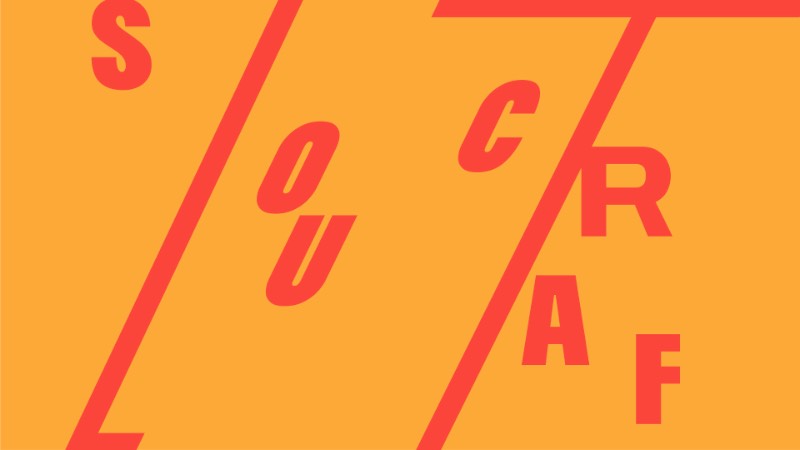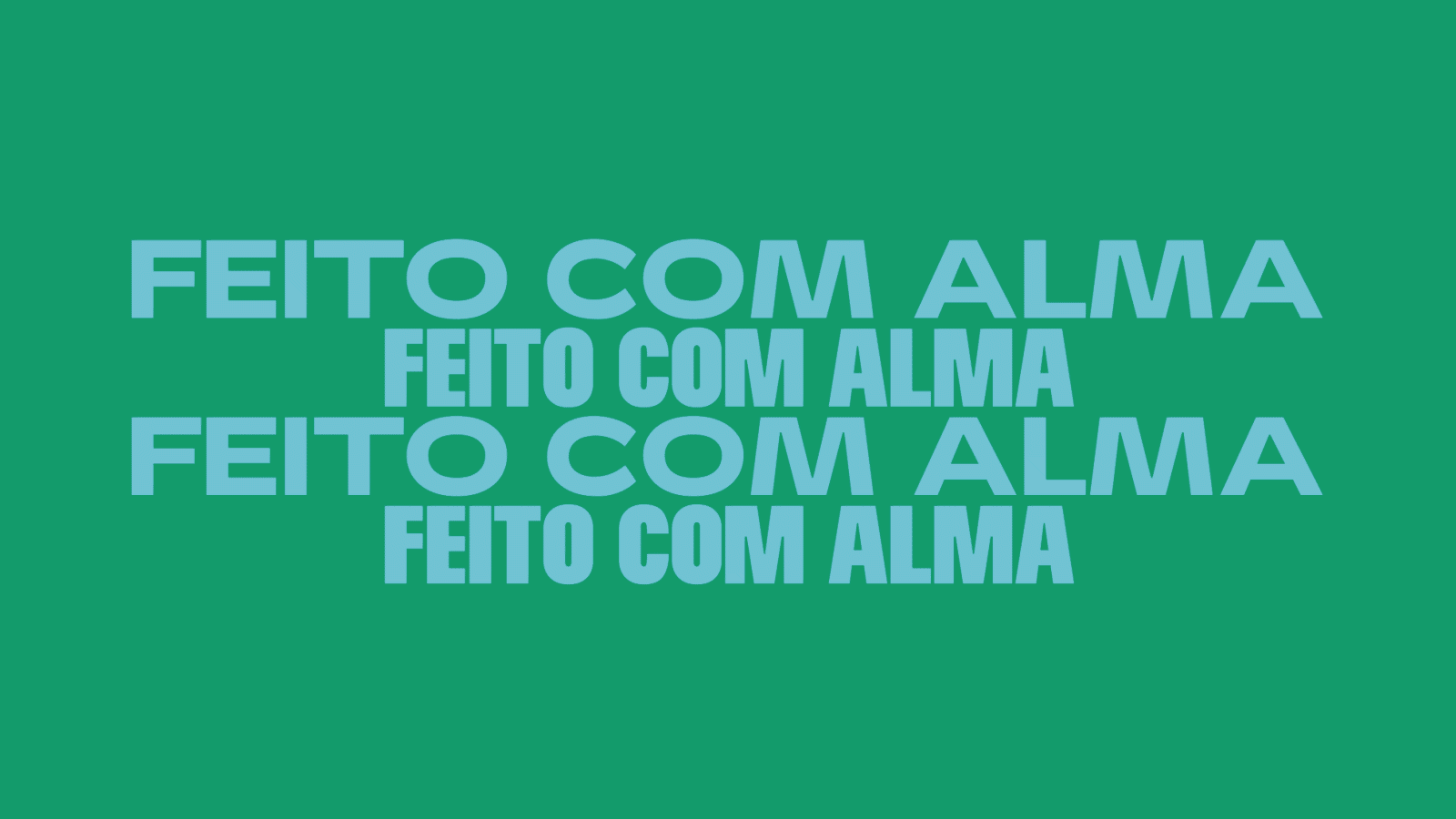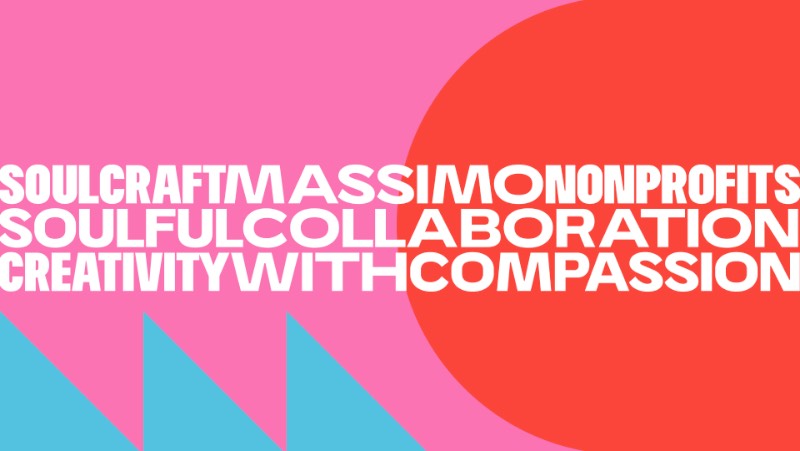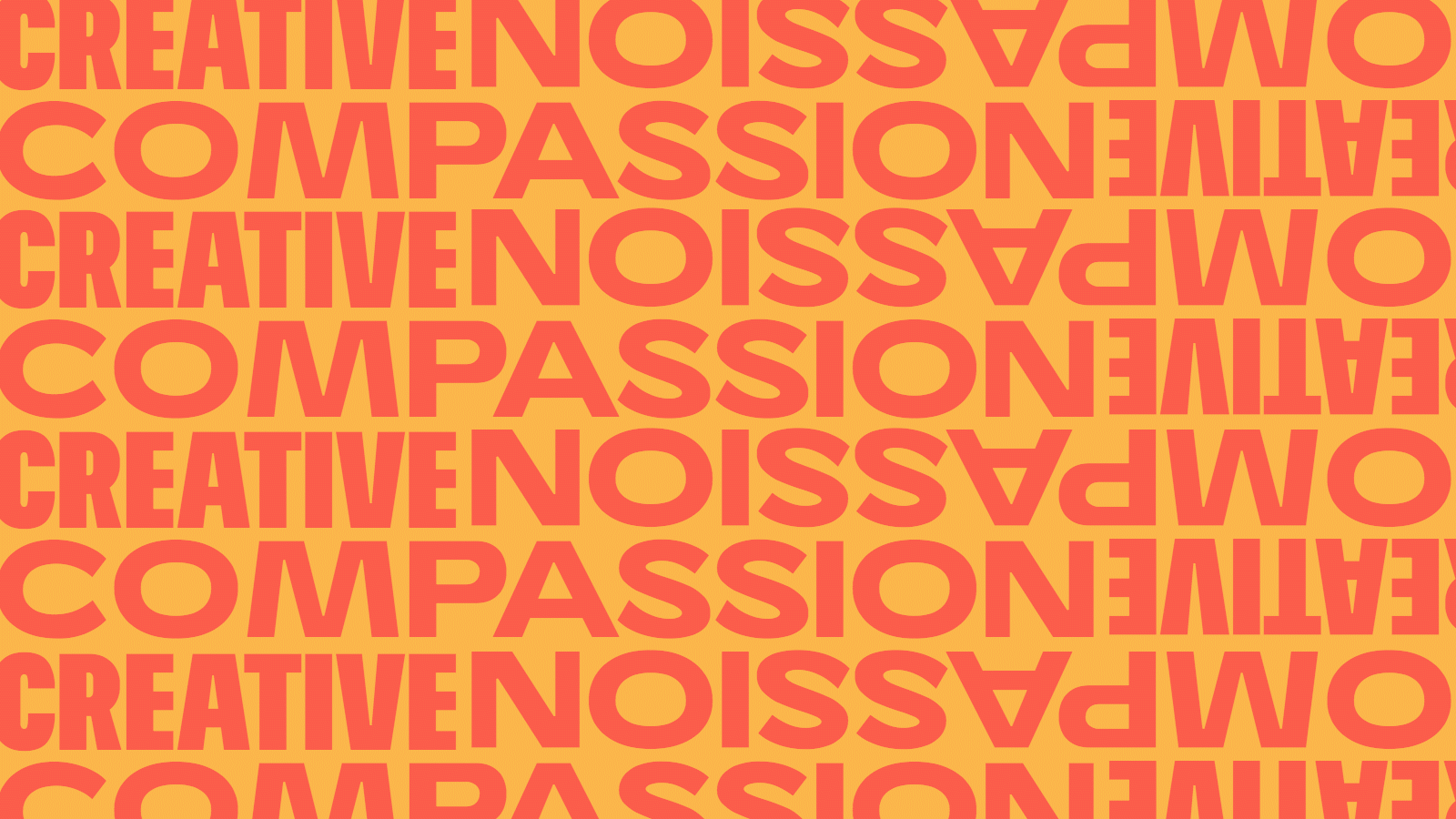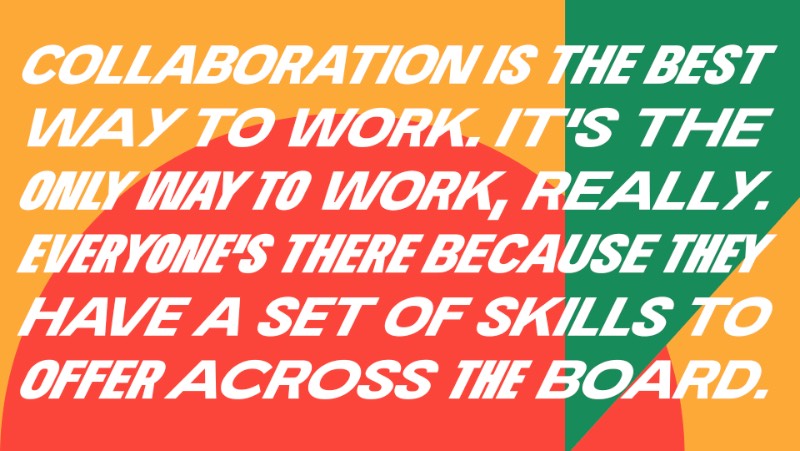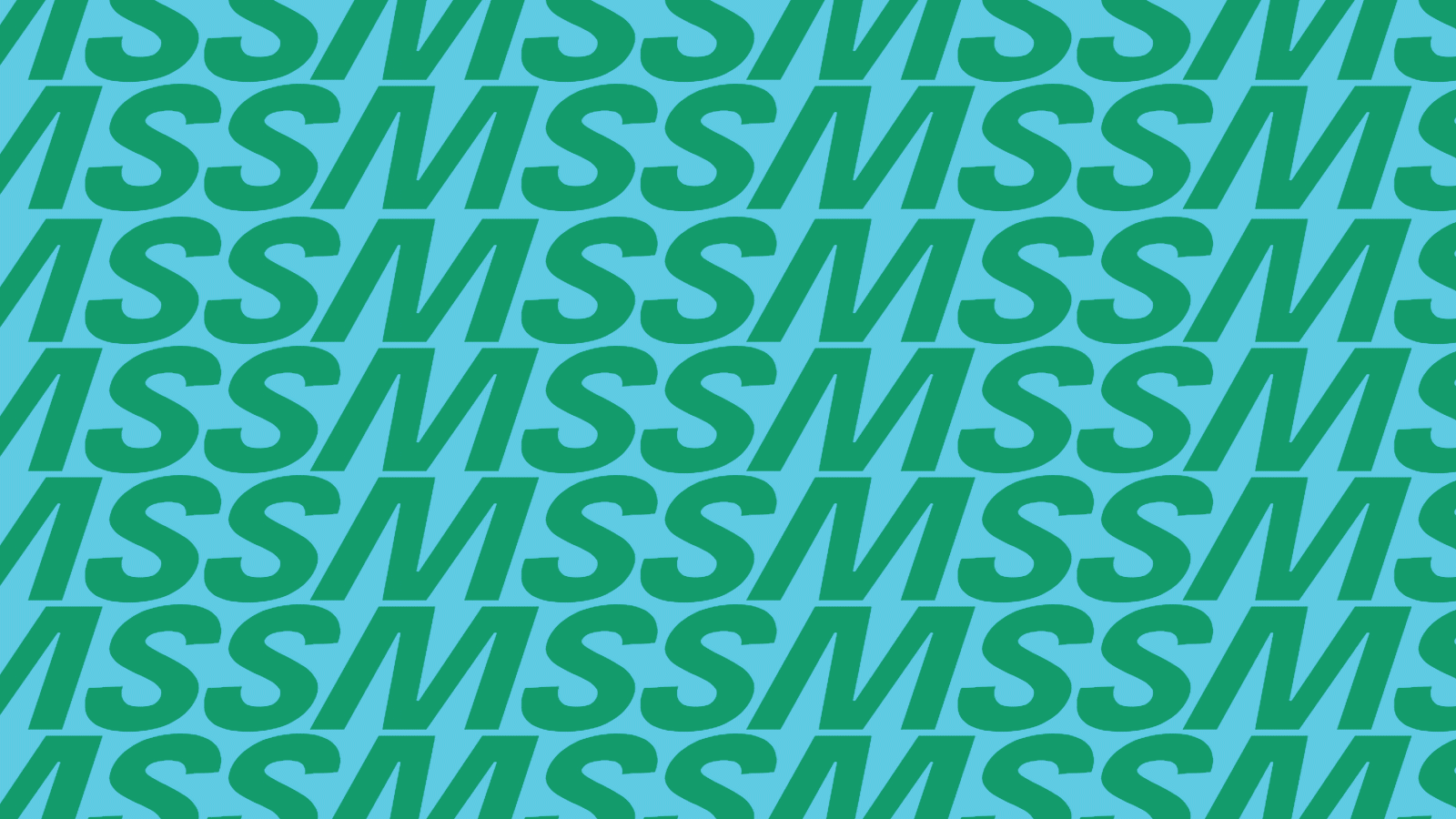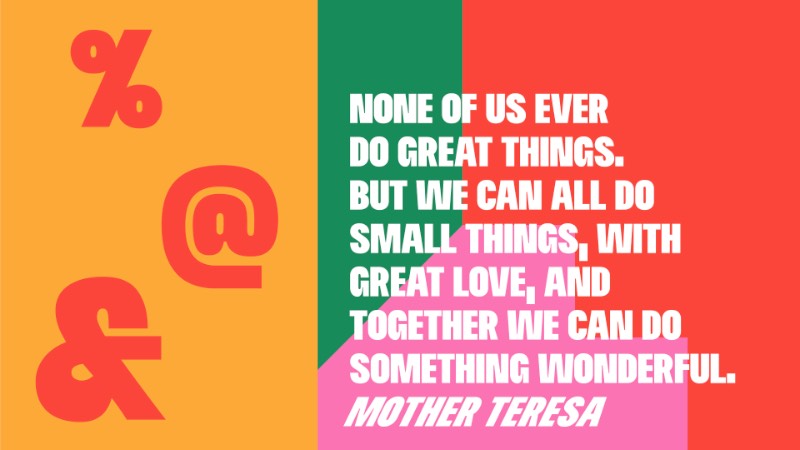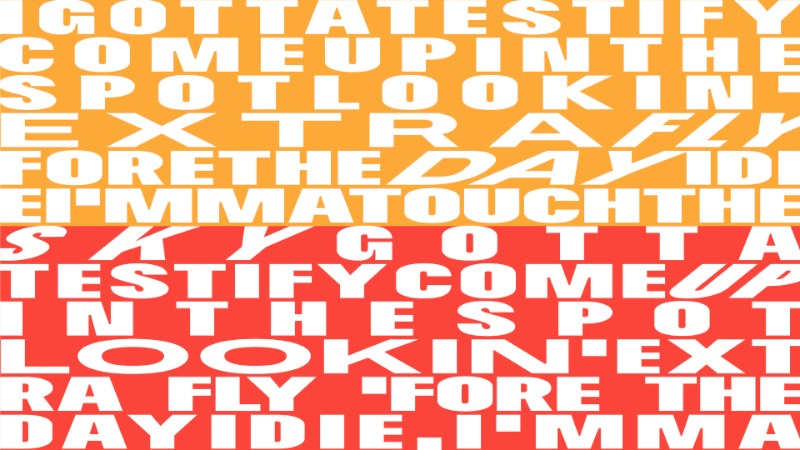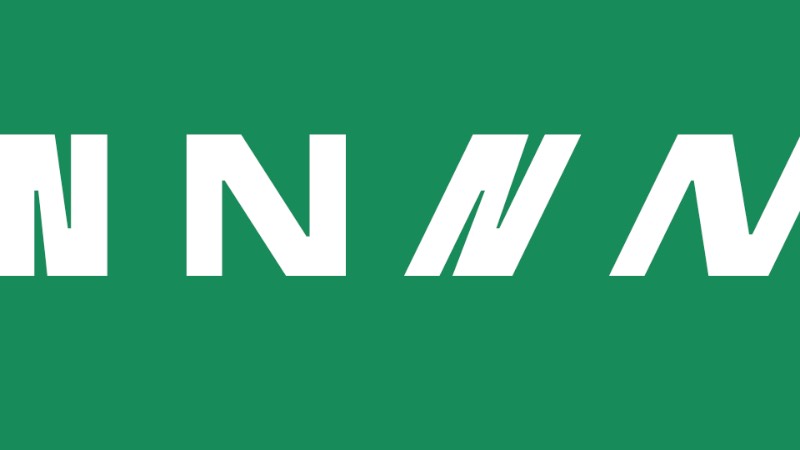
Soulcraft Typeface: A Mais Nova Fonte do Massimo Studio
Soulcraft Typeface é uma fonte desenvolvida pelo pessoal do Massimo Studio, lá de Curitiba. Essa fonte OpenType variável foi criada com a intenção de preservar e emular a tipografia vernacular, aquela tipografia local que vemos pelas paredes das cidades mas que não existem no mundo digital.
Como a Soulcraft foi criada como uma fonte OTVar, o usuário pode mudar suas largura, seu peso e suas serifas com a finalidade de criar caracteres individuais mais próximos do objetivo visual que a pessoa tem em mente. Tudo isso sem ficar dependente de uma tipografia com o peso e intensidade já definida.
Com tudo isso que existe, o designer pode replicar, de uma forma quase sem limites, todos os sinais e placas feitos a mão que você consegue encontrar pelas ruas da cidades. Afinal, com a Soulcraft, você tem uma liberdade tipográfica que é raro de observar em outras famílias tipográficas gratuitas. Ah, esqueci de falar que essa fonte é gratuita e que você pode fazer o download dela direto no link no final do artigo.
O objetivo do Massimo Studio era de criar uma fonte que encorajasse as pessoas a explorar os limites da sua criatividade. A Soulcraft Typeface foi criada para emponderar os criativos a criaram algo novo, algo que fosse mais cru e com uma voz sem travas.